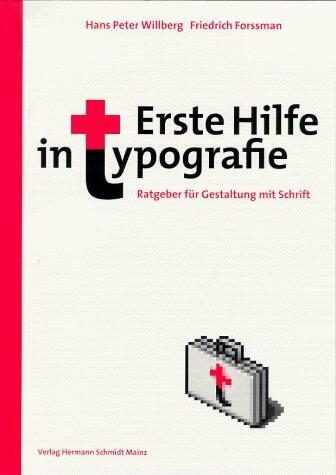
Hans Peter Willberg
Hans Peter Willberg (1930–2003) war einer der bekanntesten deutschen Buchgestalter der zweiten Hälfte des 20. Jahrhunderts. Außerdem war er als Buchillustrator und Typograf tätig. In seiner Tätigkeit als Typograf hat er die Willberg-Schriftklassifikation entwickelt. Diese Klassifikation ist neben der DIN-Klassifikation eine der wichtigsten Kriterien um Schriftarten zu kategorisieren. Sie wird von vielen der aktullen DIN-Klassifizierung bevorzugt, da mit ihr eine genauere Einordnung möglich ist.
Willberg hat unzählige Bücher gestaltet und einige wichtige Standardwerke geschrieben, z.B. »Lesetypografie«, »Erste Hilfe in Typografie«, »Wegweiser Schrift« und »Schriften erkennen«.